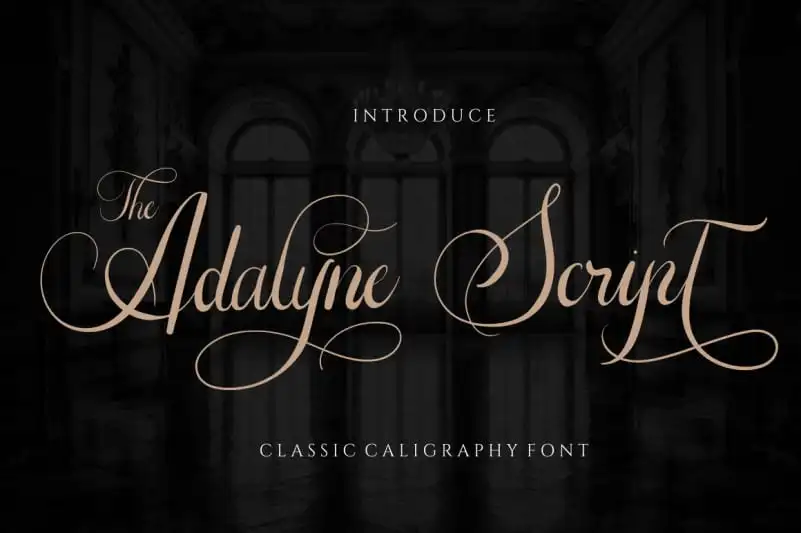
The Adalyne Script Font – Download Grátis
A fonte “The Adalyne Script Font” é uma chamada a escrita com um estilo clássico e um toque de elegância. Ela foi criada por mão humana, mantendo as características de um design clássico mas incorporando elementos modernos que a tornam perfeitamente adequada para múltiplas aplicações de design. A fonte é ideal para uso em mídia casamento, capas de livros, cartões de festa, logotipos, marca, cartões de visita e certificados. Em suma, ela se destaca como uma opção perfeita para qualquer projeto que exija um visual clássico, formal ou luxuoso. Se você está procurando por fontes com uma pegada elegante e sofisticada para suas criações gráficas, “The Adalyne Script Font” é definitivamente algo a se considerar.